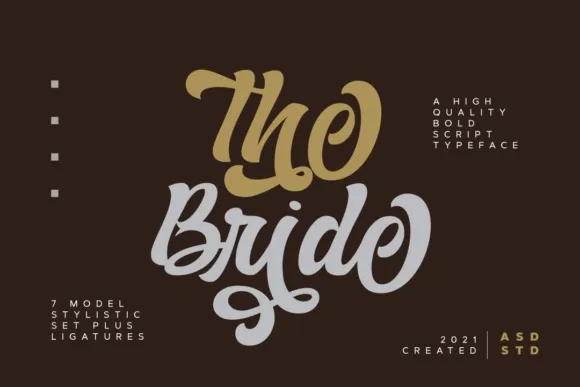
The Bride Font – Fonte Grátis
The Bride Font
A fonte “The Bride” é uma nova tipografia script moderna criada pela Asd Studio com uma baseline irregular. Este tipo de fonte é perfeitamente adaptável para diversos campos de design, incluindo anúncios de eventos, promoções de produtos, títulos de livros e ativações, logotipos, aventuras e muito mais. Com sete modelos estilizados presentes nesta fonte, ela oferece uma variedade de opções que podem transformar suas criações em designs ainda mais atraentes e belas. Se você está procurando por uma nova maneira de dar um toque único à sua identidade visual ou quer incorporar algo inovador em seu próximo projeto gráfico, “The Bride” é definitivamente um excelente investimento. Combinada com o estilo casual e divertido da bride, essa fonte cria um tom descontraído que pode ser usado tanto para design editorial como para branding de empresas, tornando-a uma escolha versátil e criativa para qualquer projeto.